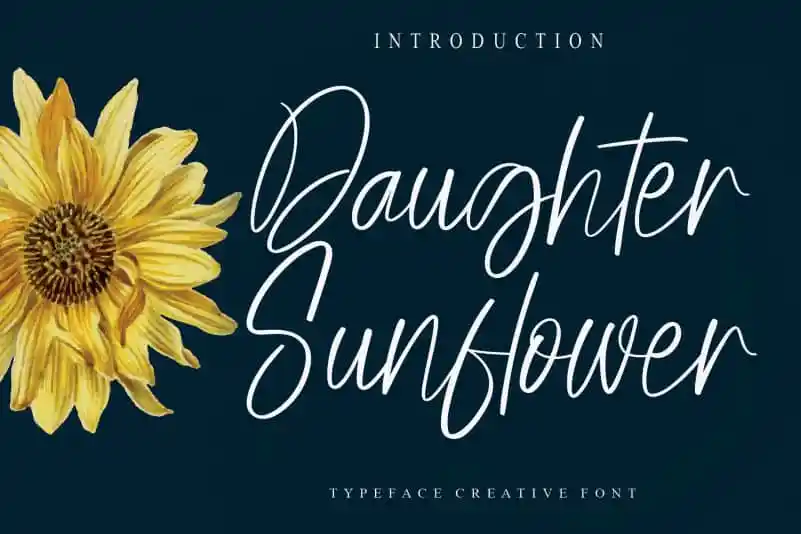
Daughter Sunflower Script Font – Fonte Grátis
Daughter Sunflower Script Font
A fonte ‘Daughter Sunflower Script Font’ oferece uma experiência visual única para designers apaixonados por estilos elegantes e sofisticados. Inspirada nos detalhes delicados das florzinhas de girassol, essa fonte é perfeita para criar textos decorativos e bem-sucedidos. Seu designer, a criatividade letter, oferece uma font que se destaca em seu uso do formato script, combinando elegância com um toque de naturalidade realista. As linhas fluidas desta font garantem que qualquer texto impresso seja irresistivelmente sofisticado e bem-sucedido, tornando-a uma escolha ideal para designers buscando dar vida a suas criações. É uma fonte criativa e especial, criada especialmente para aqueles que desejam imprimir sua marca com um toque único.